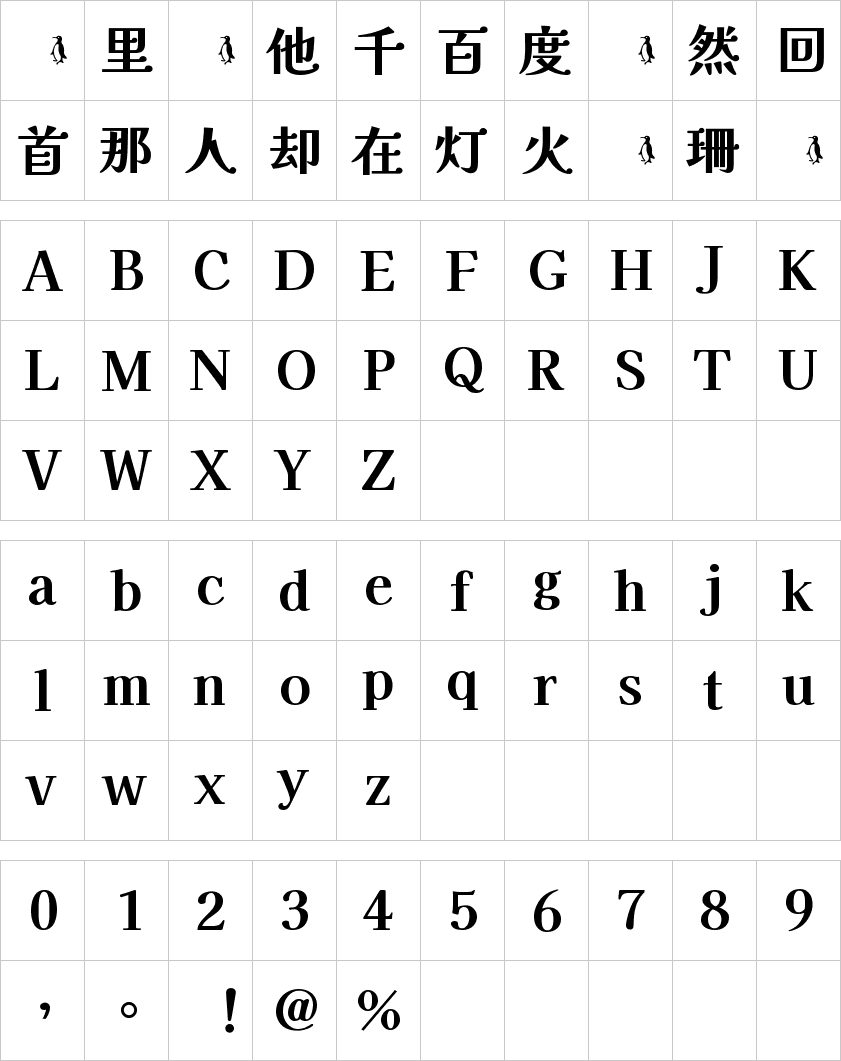
解星 EB
日语字体一般以毛笔楷书的书法为基础。日语字体有汉字(1画~20画~30画线・・・)、平假名・片假名・欧文・符号类,是一个在笔画构成上具有浓度很高的字形集合。这些浓度必须在视觉上调整。
网络社会近年来横置标记变多,而且,和其他语言也混合使用,形成了多重的字形集合。我的主题是寻找贯穿日语版蜘蛛网状隧道的光芒之路。
《解星计划》于2016年开始制作。我们通过传统的书写方法从线条构图中采用几何构图来搜索可见性。长时间摩擦过的毛笔书写方式,会变得不稳定。
在解星系列字体中,不同于传统的刷法,我们通过在右侧排列星星=点和飞溅来补偿偏离规律的不稳定性,同时导出了一个新的分量,这与传统的刷法不同。汉字的水平线比传统的明朝风格更粗。这些是为了提高电子媒体复制的可读性。